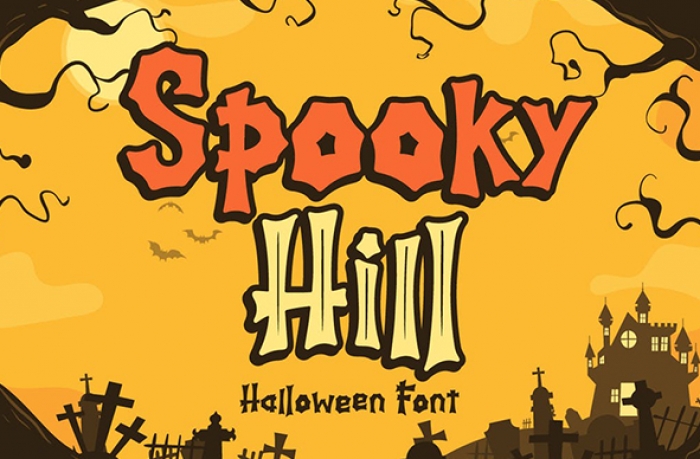
Se siete alla ricerca di idee grafiche per preparare al vostro prossimo party di halloween ecco a voi una raccolta di fonts tutti dedicati alla festa più paurosa che ci sia
In questa selezione troviamo ben 40 e oltre fonts tutti dedicati ad Halloween, da usare subito, per creare le vostre grafiche personalizzate sia in ambito privato che professionale.